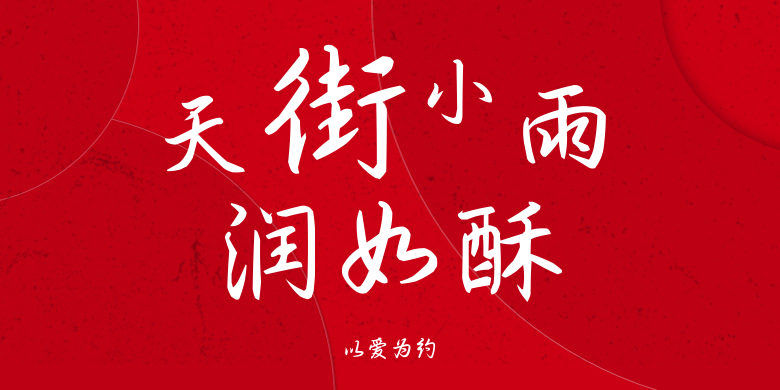
以爱为约
以爱为约,这款字体结构工整、笔画清晰,兼顾美观与易读性,适用于标题、正文、海报、包装、LOGO 等多种场景。字形优雅稳定,风格百搭耐看,适配日常排版与创意设计,让文字呈现更舒适、更具质感。以爱为约一笔一画,皆是细节,以均衡的比例、流畅的线条打造舒适视觉体验,字形端正大气,风格简约现代。无论是商业设计、品牌宣传还是日常排版,都能轻松驾驭,让文字更有格调与力量。以爱为约字体下载。